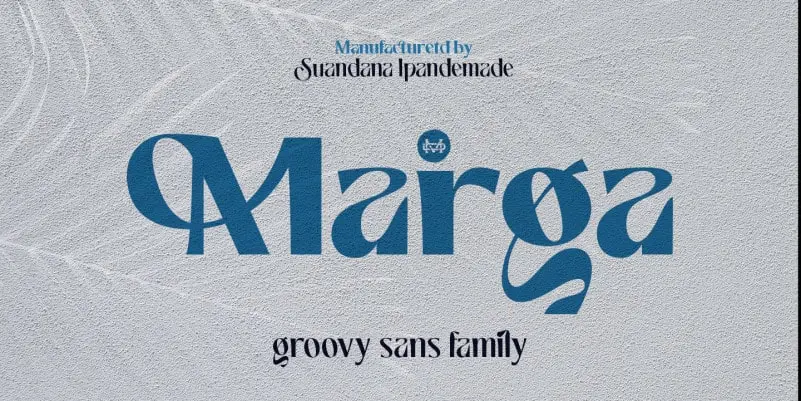
Marga – Groovy Sans Font é uma família de tipo sans-serif que traz muitas alternativas de caracteres especiais e ligaturas para dar um ar retrô ao seu design. Esta fonte traz 9 pesos variáveis, permitindo-lhe explorar inúmeras opções para criar texturas distintivas. É perfeita para uso em diversas aplicações gráficas, como design de marca, embalagens de produtos, convites, citações, etiquetas, panfletos e logotipos. Com Marga – Groovy Sans Font, você pode capturar uma atmosfera vintage enquanto adiciona um toque moderno às suas criações. Seja para trabalhos digitais ou impressos, a Marga irá destacar seu design de forma única.